¿Cuáles son las mejores fuentes para el marketing por correo electrónico?
Publicado: 2021-12-24Cuando piensa en comunicarse con sus clientes o prospectos en línea, ya sea a través de un sitio web, correo electrónico o publicidad, básicamente tiene algunas herramientas para su servicio: palabras, imágenes, colores, etc. Pero una herramienta importante que a menudo no recibe la atención que merece es la fuente que usa o el tipo de letra. Las fuentes tienen un significado psicológico visual y tienen un gran impacto en cómo los lectores perciben su contenido .
Cuando se trata de correo electrónico, a menudo depende de los especialistas en marketing elegir las fuentes correctas. Esto se debe a que no se trata solo de la fuente de su correo electrónico, sino también de la disponibilidad de fuentes en el sistema operativo y las aplicaciones de correo electrónico. Se trata de cómo se muestran sus fuentes, que eligió con un profundo conocimiento, y qué ven o no ven sus suscriptores de correo electrónico en sus correos electrónicos.
En esta guía de tipografía de correo electrónico, le presentamos las mejores fuentes de correo electrónico que necesita usar para que cualquiera pueda copiar y mostrar texto, mostrándole cómo pulir zapatos en cualquier estilo de fuente que desee y le indicamos qué tamaño y configuración de fuente usar.
¿Por qué las fuentes son importantes para el marketing por correo electrónico?
Algunas personas argumentan que la elección de la fuente no es importante o que la mejor opción es optar por las predeterminadas. Esto es un error. Los especialistas en marketing que intentan obtener el mejor resultado de sus campañas de correo electrónico no pueden permitirse el lujo de descuidar el formato y la selección de fuentes. Necesitan usar fuentes de correo electrónico para su ventaja.
Las fuentes afectan la psicología humana
Los estudios han demostrado que la fuente, el tipo de letra y el formato del texto pueden afectar las decisiones psicológicas de las personas.
En un estudio, un investigador hizo que los sujetos de prueba leyeran un texto y luego les hizo dos preguntas para evaluar sus sentimientos y opiniones sobre la información del pasaje. Los investigadores utilizaron discretamente diferentes tipos de letra para diferentes sujetos de prueba. Las fuentes probadas son Baskerville, Computer Modern, Comic Sans, Georgia, Helvetica y Trebuchet. El resultado fue que aquellos que vieron la fuente Baskerville fueron más optimistas que las personas que vieron otras fuentes en un 2%. Esto puede no parecer mucho, pero es significativo para los especialistas en marketing, especialmente porque el tamaño de la muestra fue de más de 45,000 personas.
En otro estudio, dos grupos de prueba recibieron diferentes versiones del mismo documento. Uno tenía un formato elegante, mientras que el otro era un ejemplo malintencionado de selección y formato de fuente. Los sujetos recibieron material mal formateado que mostraba claros signos de insatisfacción y negatividad.
En marketing, es importante tener en cuenta las emociones del consumidor. Los especialistas en marketing siempre quieren crear una sensación de optimismo en su mensaje. Las decisiones de compra se basan en la confianza, la fe y el optimismo.
Las fuentes afectan la capacidad de respuesta del lector
Muchos especialistas en marketing temen que su copia no se lea. Las personas que tienen un sentimiento positivo desde el principio seguirán leyendo, mientras que las que se aburran o se frustren se irán en segundos. La elección del tipo de letra y el tamaño de fuente influye en gran medida en si sus lectores siguen leyendo.
Los tamaños de fuente más grandes significan que todos pueden leer más cómodamente. Este confort se correlaciona con emociones positivas que hacen que el lector esté más dispuesto a seguir leyendo y convirtiendo. La regla se aplica a papeles, pantallas de computadora y dispositivos móviles.
Sin embargo, hay un límite a la ventaja de las fuentes más grandes. Si publica el cuerpo del texto en una fuente de 36 puntos, es como si un niño lo triturara. Las personas sentirán que los textos los atacan, y desplazarse por ellos parecerá molesto. Como regla general, mantenga todo el texto del cuerpo por debajo de los 18 puntos y todo el texto del título por debajo de los 36 puntos.
Las fuentes afectan la atención
La importancia de la selección y el tamaño de la fuente parece bastante simple, pero el espacio entre líneas también tiene un gran efecto en la atención de las personas. Las personas a menudo escanean los correos electrónicos en lugar de leerlos directamente, y los saltos de línea hacen que los lectores capten los puntos principales y los lean con más atención. Una pared de texto a menudo es frustrante de leer. Al darse cuenta del efecto del espacio entre líneas en el comportamiento del lector, los especialistas en marketing usan saltos de párrafo con más frecuencia que otros escritores.
Sin embargo, hay otro aspecto del espaciado que es importante, y es el espaciado real del texto entre líneas.
Dependiendo de la plataforma de correo electrónico que esté utilizando, dejar el espacio entre líneas en la configuración predeterminada puede significar que está escribiendo con líneas de espacio simple. Un gran problema con las líneas de espacio simple es que actúan como grandes bloques de texto. Cuando el lector ve más de tres líneas separadas, tiende a molestarse e ignorarlas.
Para que esto no suceda, te recomendamos cambiar el interlineado a 1,4 o 1,5 en lugar de 1,0. Esto proporcionará un amplio espacio para que sus oraciones respiren y permitirá que las personas entiendan su escritura. Si tiene un texto claro y un fondo oscuro, considere aumentarlo a alrededor de 1,7. Sin embargo, no se preocupe demasiado por el espacio entre líneas. Algunos especialistas en marketing parecen pensar que tener más espacio siempre es algo bueno, pero no es así. Si el interlineado es 2.0 o más, su texto se verá desorganizado. Tal espaciado interrumpe la continuidad de la imagen y dificulta que los lectores sigan el desarrollo de su idea.
Lee mas:
- Las 13 mejores fuentes para tus tiendas Shopify
- ¿Por qué P/S es imprescindible en el marketing por correo electrónico?
¿Cómo seleccionar las mejores fuentes para email marketing?
Aquí hay una lista completa de fuentes admitidas por la mayoría de los proveedores de servicios de correo electrónico:
Arial, Arial Black, Courier New, Comic Sans, Georgia, Impact, Book Antiqua, Palatino, Tahoma, Geneva, Times, Times New Roman, Trebuchet MS, Charcoal, Lucida Console, Lucida Sans Unicode, Lucida Grande, Palatino Linotype, Helvetica, Verdana, Mónaco.
Como puede notar, no hay muchas opciones para usar. Para la copia del cuerpo principal de su correo electrónico, necesita tipos de letra compatibles que sean legibles y complementarios. No desea desviar la atención de los lectores de ningún texto visible que pueda incluirse: su oferta, su titular y título, y las palabras en sus botones.
Le daremos la respuesta de inmediato: no hay una fuente o tipo de letra adecuado. Por eso existen las opciones. Al igual que con diferentes colores, fuentes y tipos de letra atraen diferentes emociones. Las personas que elija deben atraer al grupo demográfico específico al que se dirige.
Con eso en mente, aquí está mi selección de las mejores fuentes de correo electrónico para usar para una legibilidad y neutralidad óptimas:
Georgia
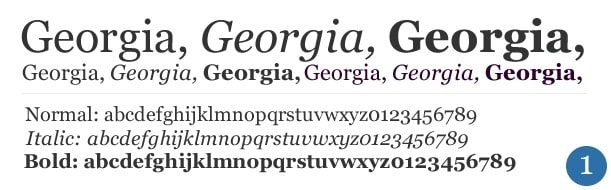
Georgia es una fuente serif (lo que significa que tiene algunos rizos o rápidos al final de las letras). Diseñado en 1993 para Microsoft, está inspirado en los tipos de letra Scotch-Roman originales utilizados en la impresión. Tiene una estética autoritaria 'clásica' después de haber sido utilizada en novelas y periódicos. Es uno de los más fáciles de leer, con espaciado uniforme entre letras y serifas gruesas que sirven como guía para sus ojos a medida que avanza por la página.
La intención de Georgia era tener un tipo de letra que se viera elegante y amigable mientras se mostraba bien en pantallas pequeñas o de baja resolución. Es muy parecido a Times New Roman, excepto que se siente más grande y redondeado.
Times New Roman
Durante un tiempo, Times New Roman fue el tipo de letra serif más utilizado en el mundo. Un tipo de letra serif es un tipo de letra alado en las esquinas de las letras. Times New Roman fue creado por el periódico británico The Times en 1931. Un diseño con serifa es pesado y el peso de las líneas contrastantes (por ejemplo, el espacio corto en la parte inferior de la letra "T" es mucho más delgado que la línea que conduce a it), que ayuda a dirigir la mirada del lector de una letra a otra.
Su familiaridad hizo que Times New Roman fuera realmente popular: hasta 2007, era la fuente predeterminada para todas las versiones de Microsoft Office y muchos otros procesadores de texto. Puede usarlo para un tono serio, clásico y prestigioso consistente con el uso habitual de los documentos oficiales.
Arial
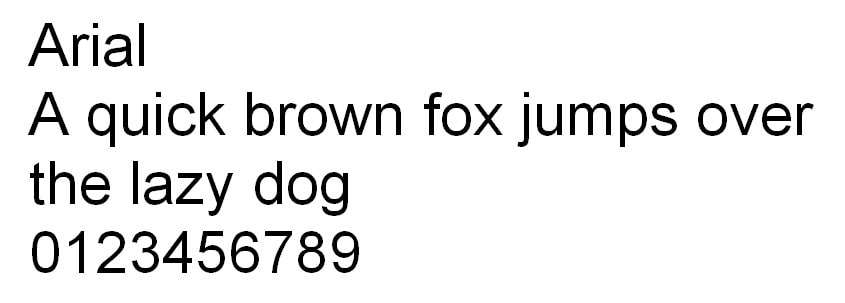
Arial se introdujo en 1982 para servir como una alternativa gratuita a la popular Helvetica. Arial es la fuente de mucho debate sobre la copia web y el correo electrónico. Si bien muchos fabricantes de software y proveedores de correo electrónico lo usan de forma predeterminada, a algunos diseñadores les resulta difícil de leer, con las letras colocadas demasiado juntas, como ocurre con Helvetica.
Las letras similares parecen tener los mismos ángulos y líneas, lo que dificulta distinguirlas en párrafos de texto grandes. Sin embargo, muchos diseñadores aprecian Arial como una gran fuente para complementar un tono no invasivo, humilde y reconocible de su uso popular como software predeterminado.
verdana
La fuente Verdana, que lleva el nombre de la hija del diseñador, es una combinación de las palabras "verdant" (algo verde) y "Ana" (su nombre). Esta es una de las fuentes web seguras sans-serif más fáciles de leer. Las letras de una forma similar están diseñadas para parecer diferentes, en particular, para aumentar la legibilidad general. Las letras minúsculas más altas son típicas de este tipo de fuente, por lo que puede ser una gran fuente para garantizar que su copia tipográfica sea accesible para todas las edades y habilidades.
El gran beneficio de los tipos de letra sans-serif es que pueden transmitir una sensación de diversión y dignidad. Si eso es lo que está haciendo en el marketing de sus boletines, Verdana es probablemente la mejor opción para el contenido textual.
Trabuquete MS
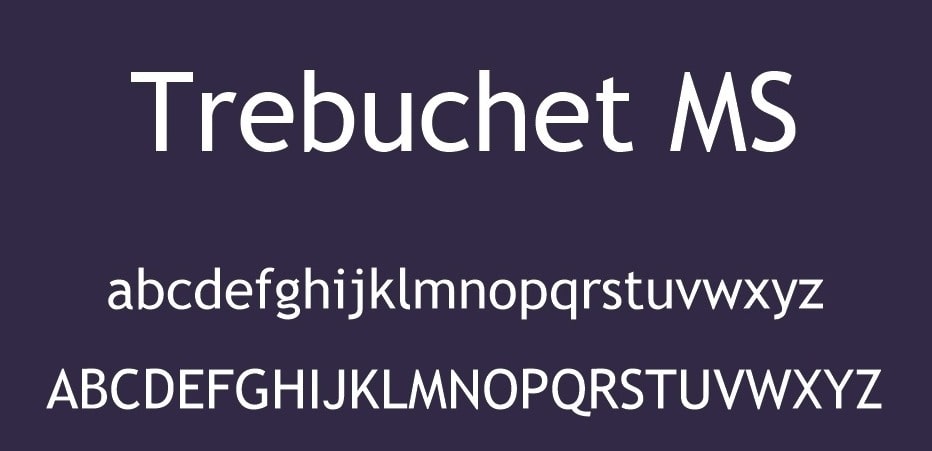
Cuando Vincent Connare diseñó esta fuente, la llamó "Trebuchet", una catapulta medieval. Pensó que Trebuchet sería un nombre excelente para una fuente capaz de introducir palabras en Internet. Y no se equivocó. Trebuchet es actualmente una de las mejores fuentes para usar en marketing por correo electrónico.
Tiene pequeños trazos precisos al principio y al final de las letras difíciles que sirven como una guía fácil de leer sin distraer demasiado la forma principal de las letras, como con la corrección completa de las serifas.
Tahoma
Esta fuente sans-serif ampliamente utilizada llamada Tahoma es perfecta para los especialistas en marketing que necesitan escribir boletines por correo electrónico en otros idiomas además del inglés. A diferencia de otras fuentes de Internet ampliamente utilizadas como Georgia y Verdana, tiene un conjunto completo de caracteres Unicode. Esto significa que Tahoma es compatible con caracteres asiáticos y otros caracteres no latinos y letras latinas con acentos.
Sin embargo, un problema con Tahoma es que no es tan compatible como otras fuentes de Internet populares como Georgia y Verdana. Puede haber un problema de compatibilidad, con caracteres que se muestran como falsos.
mensajero
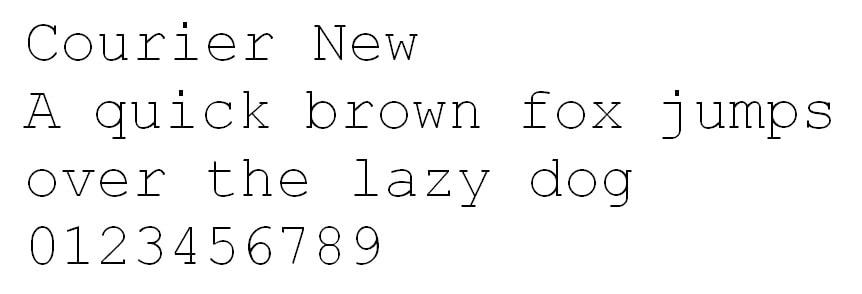
El tipo de letra Courier serif es monoespaciado, lo que significa que cada letra o puntuación ocupa la misma cantidad de espacio horizontal en la página. La fuente Courier no es agradable a la vista en comparación con otros tipos de letra populares en esta lista. Sin embargo, su principal ventaja radica en el hecho de que, al ser monoespaciado, Courier se organiza fácilmente en ordenadas columnas horizontales.
Si bien a los especialistas en marketing a menudo no les gustan los tipos de letra Courier, puede haber nichos de mercado para que coincida. Si está comercializando específicamente para escritores, es posible que se sientan atraídos por esta fuente, ya que parece un documento escrito en una máquina de escribir. Esto puede impartir una estética rústica y amigable.
Independientemente de las fuentes seguras para la web que utilice, tenga en cuenta lo que hacen. Los tipos de letra compatibles entre sí se configuran hasta el punto en que se consideran más obvios que la mayoría. Pueden hundirse en la página y pasar desapercibidos. Esto significa que sus lectores pueden concentrarse más en su contenido que en cómo lo presenta, lo cual es especialmente esencial con copias más largas.
Afortunadamente, puede encontrar las 7 fuentes anteriores en nuestro panel de control de la aplicación de marketing por correo electrónico. Puede editar las fuentes tanto para el título como para el cuerpo del texto para tener la mejor influencia en los destinatarios.
Consejos adicionales sobre fuentes de marketing por correo electrónico
Algunos diseñadores tienen una cosa para las fuentes personalizadas. También necesitan redundancia para aparecer en todos los sistemas y aplicaciones de correo electrónico. Siempre revise sus correos electrónicos para verificar la visualización de fuentes y la redundancia. Aquí hay algunos consejos adicionales para ayudarlo a seleccionar y usar las mejores fuentes para el marketing por correo electrónico.
colores de fuente
El color del texto ayuda a que su mensaje se destaque. Sin embargo, restringir el uso del color es la mejor opción. Tres es el límite: uno para el título, otro para el resto del texto y otro para resaltar los enlaces.
Además, el color que elija debe tener un contraste lo suficientemente alto con el color de fondo para aumentar la legibilidad.
Tamaños de fuente
Después de trabajar arduamente para elegir las mejores fuentes, es una tragedia que el texto parezca demasiado pequeño o demasiado grande para leerlo. Pero puede ser difícil saber cómo aparecerá el tamaño del texto HTML en vivo para los diferentes destinatarios. Aquí hay una guía útil sobre los tamaños de fuente y las alturas de las líneas para usar en el texto multiplataforma más fácil de leer.
Título : 22 - 28 píxeles
Texto de contenido : 14 - 18 píxeles
Altura de la línea : 1,4 - 1,5
El tamaño de su texto será diferente según la fuente que use, así que pruebe con los valores en este rango recomendado y vea qué funciona mejor para usted. Siempre envíese versiones de prueba de su correo electrónico para verificar las variaciones y la consistencia deseada. Pruebe y vuelva a verificar para asegurarse de que su texto sea claro en todos los dispositivos y todas las aplicaciones de correo electrónico.
Mezclar tipos de letra
Reconociendo el hecho de que los diferentes tipos de letra tienen ventajas y desventajas, algunos especialistas en marketing pueden considerar usar una combinación de ellos en su marketing por correo electrónico. Como sea, esto no es recomendable. Como máximo, debe usar dos tipos de letra: uno para el título y el texto del título y otro para el texto del cuerpo.
Un problema con el uso de demasiados tipos de letra en el marketing por correo electrónico es que molesta al lector. El resultado que aparece es cacofónico. Todos los lectores tienen el corazón roto: quieren deshacerse de él lo antes posible. El mismo efecto cuando los especialistas en marketing crean un arcoíris con diferentes colores en su texto: esta también es una mala elección. Otro problema que surge cuando se utilizan tres o más tipos de letra diferentes es que los proveedores de servicios de correo electrónico pueden marcar los mensajes como spam.
Pruebas A/B
Si no está seguro de cuál es la mejor fuente para su mercado objetivo, una cosa que puede hacer es usar su proveedor de marketing por correo electrónico para realizar pruebas A / B.
Para implementar las pruebas A / B, cree dos versiones de su boletín donde todo sea idéntico excepto la fuente. Luego mida las respuestas de los destinatarios según la fuente que eligió. Puede utilizar esta información para tomar mejores decisiones sobre fuentes en el futuro.
tipografías raras
Así que encontraste la fuente perfecta. ¡No tan rápido! En muchos casos, puede no ser fácil usar el tipo de letra de su elección en su correo electrónico. En Gmail, solo puede usar entre Sans Serif (como Helvetica), Ancho fijo (como Courier), Serif (como Times New Roman), Garamond, Georgia, Tahoma, Trebuchet MS, Wide Narrow, Comic Sans MS y Verdana. Así que asegúrese de que sus fuentes sean buenas para las plataformas de los destinatarios.
Consejos finales